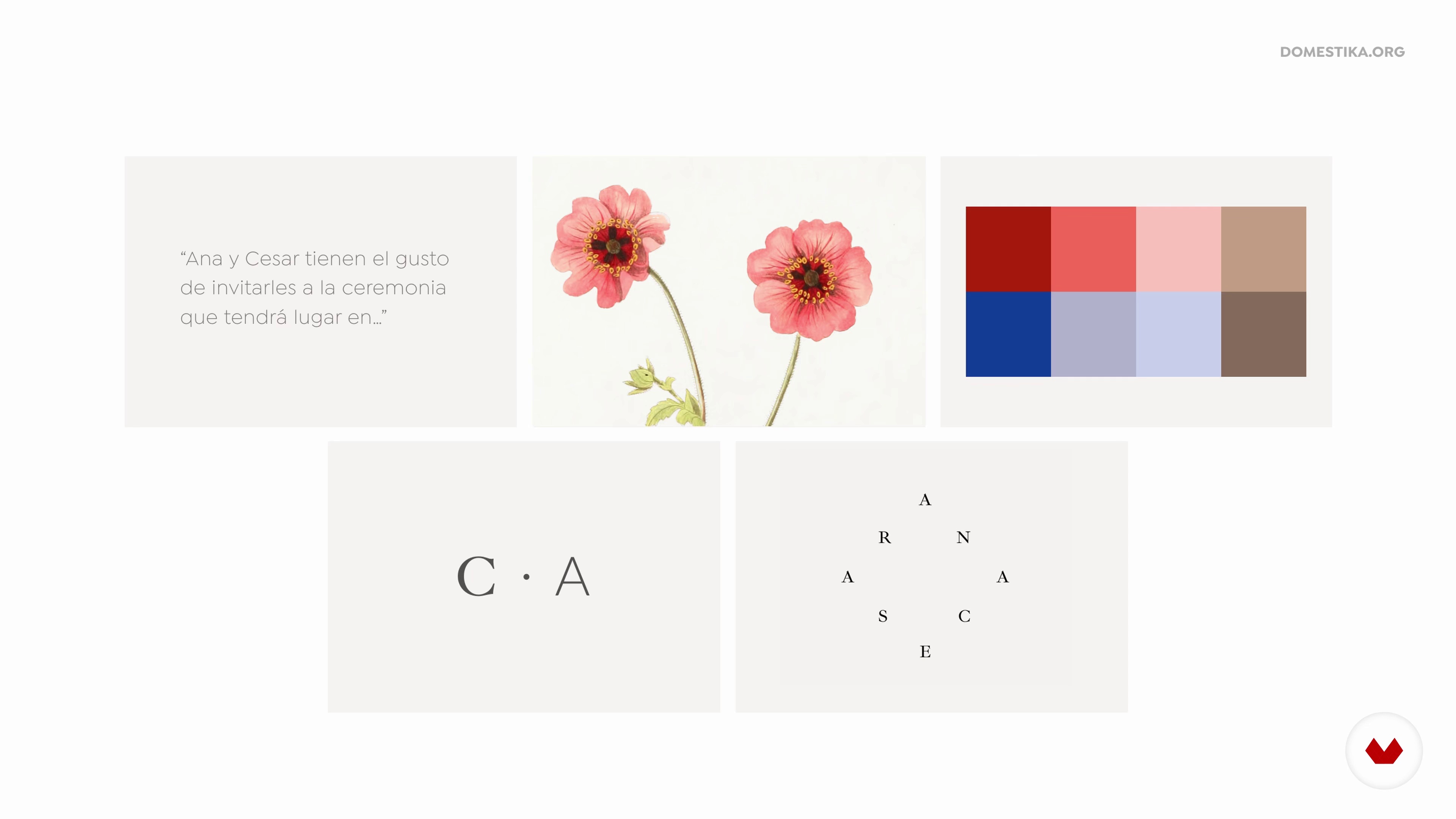
Design von Event-Einladungen
Visuelle Identität: Typografie und Symbol
Über die Videolektion: Visuelle Identität: Typografie und Symbol
“Nun wollen wir sehen, wie man Schriftarten auswählt. Ich werde Ihnen erklären, dass jeder seinen eigenen Stil hat und dass daher jede Schrift etwas anderes sagt. Später werde ich Ihnen einige Stellen zeigen, an denen Sie Schriftfamilien für Ihr Projekt finden können. Ich werde Ihnen auch einige Tricks erklären und in Illustrator prüfen, ob die von uns ausgewählten Schriftarten gut funktionieren. Als nächstes werden wir daran arbeiten, ein Symbol wie beispielsweise ein Monogramm oder ein Piktogramm zu erstellen. ”
In dieser Videolektion behandelt María Design (The Visual Romance) das Thema: Visuelle Identität: Typografie und Symbol, das Teil dieses Domestika-Onlinekurses ist: Design von Event-Einladungen. Lerne von Grund auf, wie man auffällige Einladungen für Events gestaltet .
“Visuelle Identität: Typografie und Symbol Wir haben bereits drei der fünf Elemente gesehen das wird Teil der visuellen Identität sein. Jetzt konzentrieren wir uns auf Typografie. Ich werde Ihnen Tipps zur Auswahl geben. Dann konzentrieren wir uns auf die Erstellung eines Symbols. Wir werden verschiedene Optionen analysieren und wir werden auswählen, was am besten zu den Einladungen passt. Ich werde es dir zeigen. Ich habe bereits drei der fünf Elemente meiner Identität definiert. Ich definierte den Tonfall. Ich habe einen Grafikstil gewählt und die Farbpalette ausgewählt. Jetzt werde ich mi...”